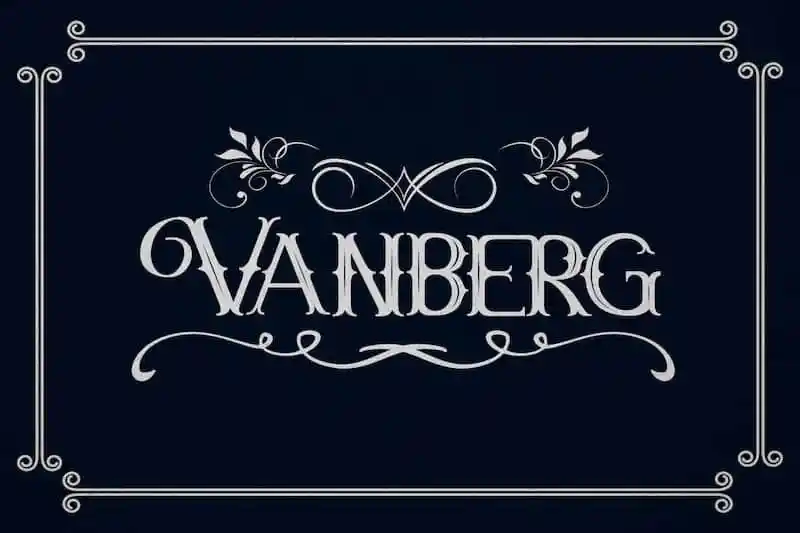
Vanberg Display Font – Download Grátis
Vanberg Display Font é uma tipografia para uso em exibição que incorpora elementos vintage com a delicadeza moderna. Essa fonte retrata a essência de um design Victoriano, misturando o clássico e o contemporâneo. Ela foi projetada e compartilhada pela Maulana Creative. Vanberg Vintage é uma mão-dura letra Victoriana modernizada que mescla tipografia antiga e atual com alternativas incríveis. Este tipo de exibição proporciona um contraste atraente entre as características vintage clássicas e o estilo sofisticado contemporâneo da Vanberg Display Font, criando um visual que vai brilhar em qualquer design impresso ou digital.